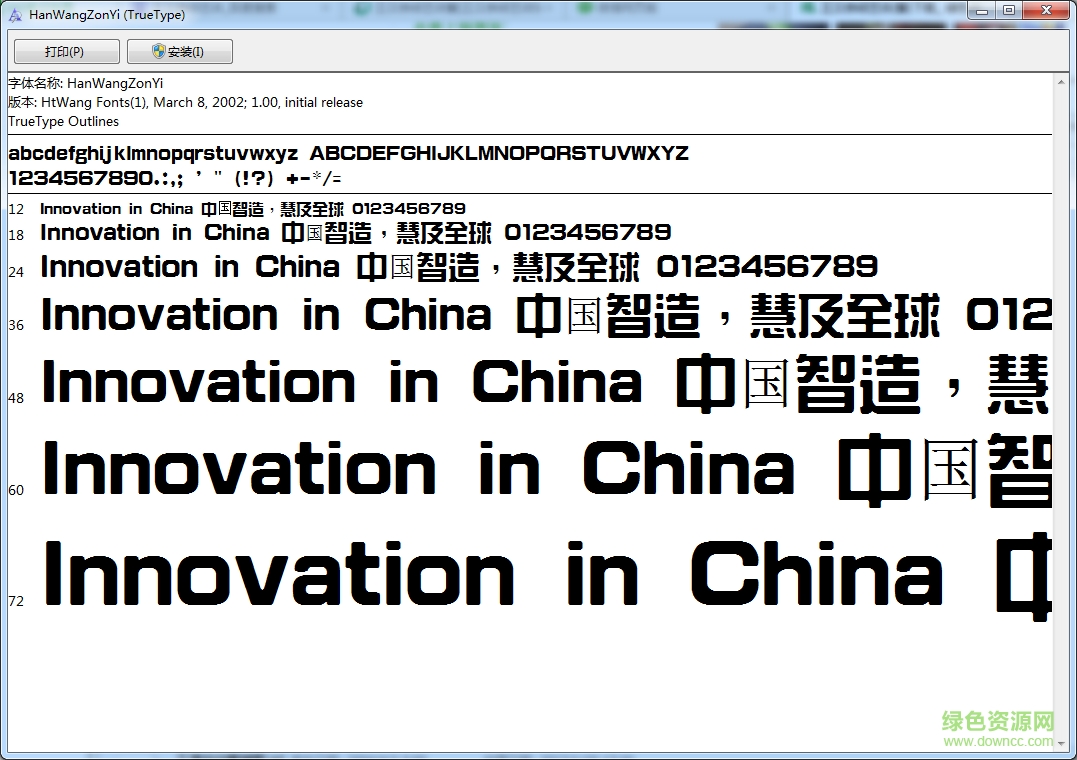
王漢宗綜藝體
王漢宗綜藝體是一款應用領域非常廣泛的電腦字體軟件,文字粗細錯落,非常的獨特和醒目,字體端莊大氣使用便捷獨具美感。喜愛的朋友快來綠色資源網下載體驗吧!
王漢宗綜藝體是一款專門用于美工設計方面的電腦字體,改字體瀟灑俊逸、自然舒展,讓人賞心悅目,整體效果非常的統(tǒng)一,而且字庫完整,喜歡的用戶可以來體驗。